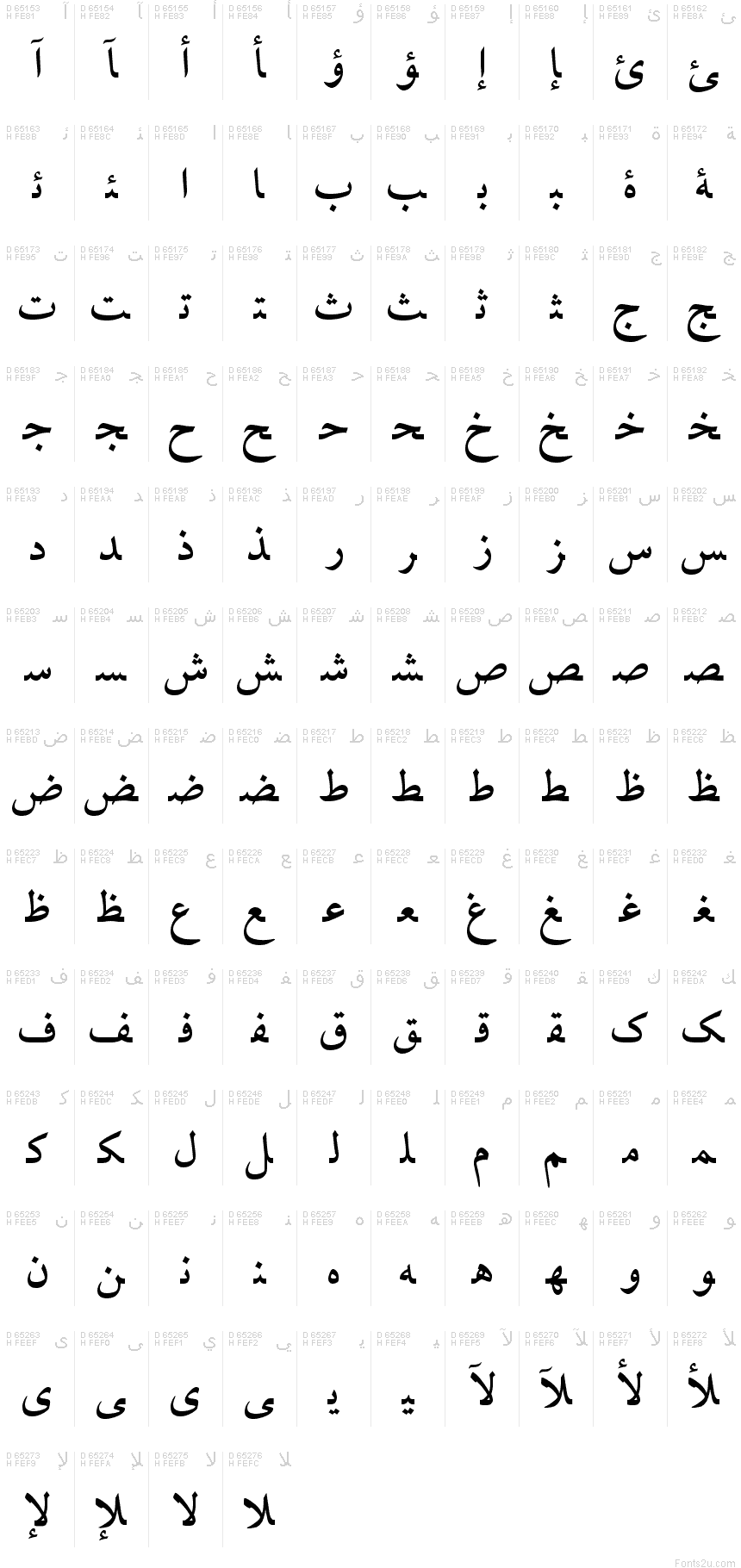
B Lotus Bold, di Borna Rayaneh, è un carattere arabo display gratuito, caratterizzato da un ritmo calligrafico compatto e da un'estetica marcatamente ornamentale. Le lettere sembrano costruite con forme dense e arrotondate, con tagli a cuneo e giunzioni strette, conferendo al segno grafico una presenza scultorea ed emblematica, piuttosto che un aspetto da scrittura a mano fluida.
Questo lo rende perfetto per testate, poster culturali, packaging, copertine di libri, titoli e marchi dove il carattere deve definire da solo l'atmosfera. Essendo un font gratuito, si presta ottimamente a contesti brevi e d'impatto, ideale quando cerchi una tipografia araba che risulti solida, decorativa e dal fascino cerimoniale.